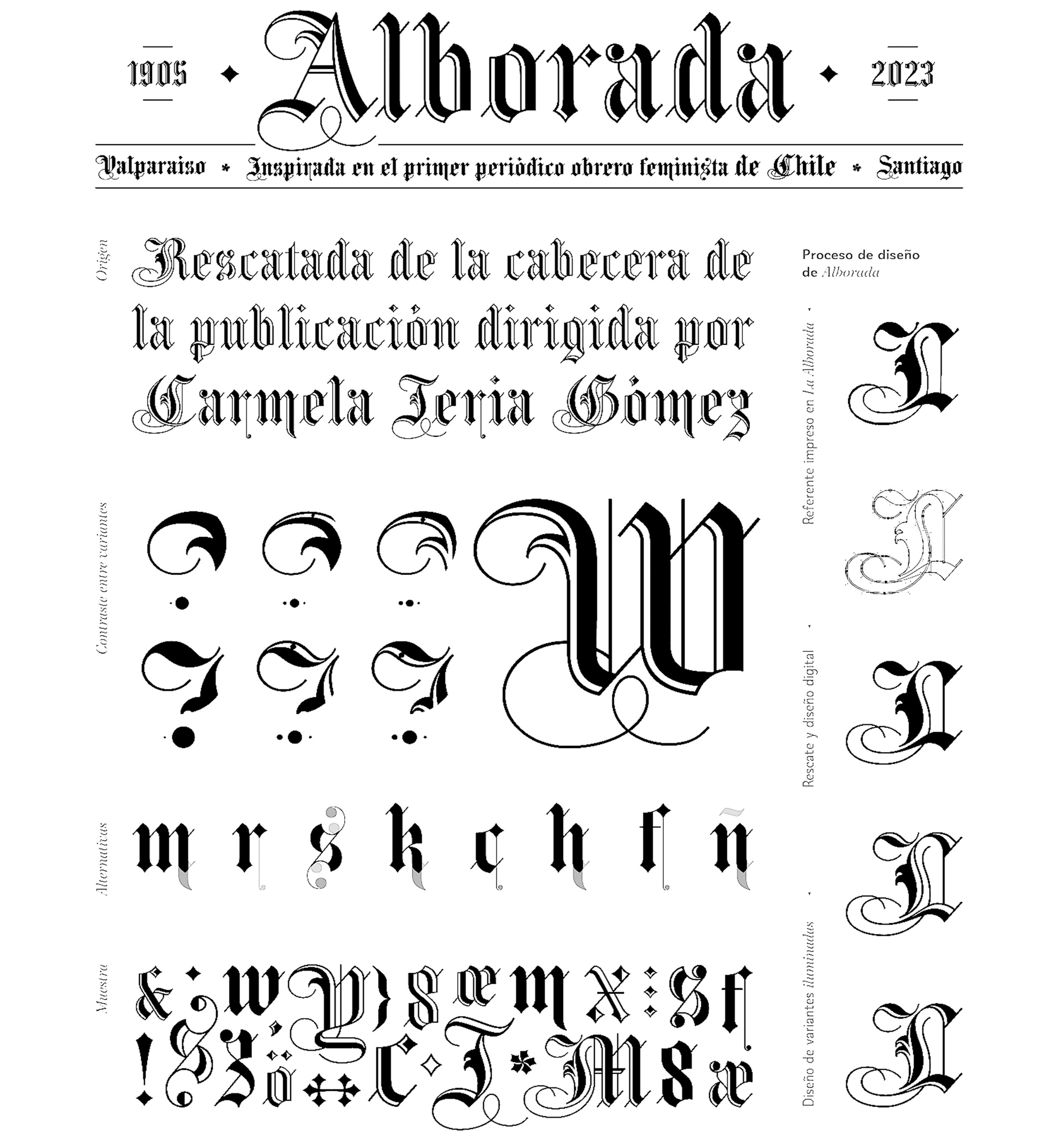
Alborada es una fuente digital desarrollada por la diseñadora chilena Camila Ríos Palma, coatura del libro Carmela y La Alborada.
Esta fuente digital es un rescate tipográfico histórico de la tipografía utilizada para componer la cabecera del primer periódico obrero feminista de Chile La Alborada de la tipógrafa Carmela Jeria Gómez en 1905. La propaganda feminista de Jeria, estuvo estrechamente vinculada con la ilustración, siendo esta la base conceptual para desarrollar dos variantes de la fuente digital bajo el concepto de iluminación. Finalmente se obtiene una versión digital a partir de las ocho letras impresas en el periódico y dos variantes referenciando la iluminación que debía alcanzar la mujer chilena para lograr la emancipación.
La motivación de Camila para diseñar esta fuente fue visibilizar y poner en valor el legado tipográfico de las mujeres chilenas; específicamente, el de una figura femenina invisibilizada, pionera en el quehacer tipográfico y en el desarrollo de temáticas feminista-obreras en Chile.